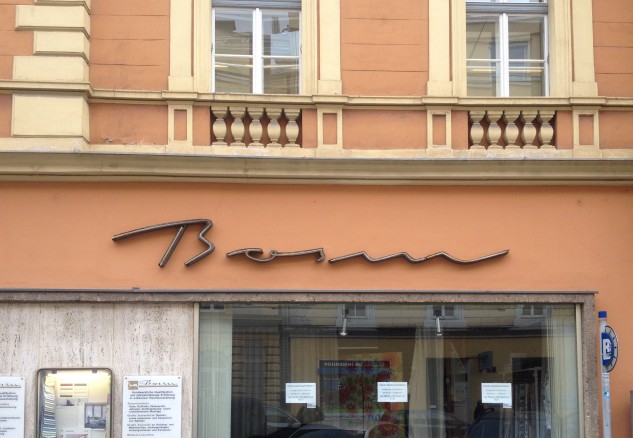
Bosin
Der wie eine Signatur locker hingeworfene Schriftzug auf der Fassade des Textilgeschäfts "Bosin" spiegelt eleganten 50er-Jahre-Flair wider und passt damit besonders gut zum Portal des Hauses und der Innenausstattung des Geschäfts. Architektur und Typografie gehen hier eine schöne Symbiose ein. Wieder ein Meisterwerk von Arthur Zelger, der ums Eck sein Atelier hatte. Eine qualitätvolle Signatur, die auch hier für die Qualität des Hauses stehen sollte.
Das Geschäft wurde kürzlich aufgelassen, leider konnte – trotz versuchter Intervention – die Schrift nicht gerettet werden. Eine Zeitlang war sie als Ghostletter noch zu sehen. Hier kehrte das Private aus der Öffentlichkeit wieder ins Private zurück – es war der Besitzerin vielleicht nicht recht, mit dem Schriftzug auch ihren Namen in unbekannte Hände zu geben. Vielleicht verständlich, aber schade um die schöne Arbeit ...
Innsbruck, Fallmerayerstraße